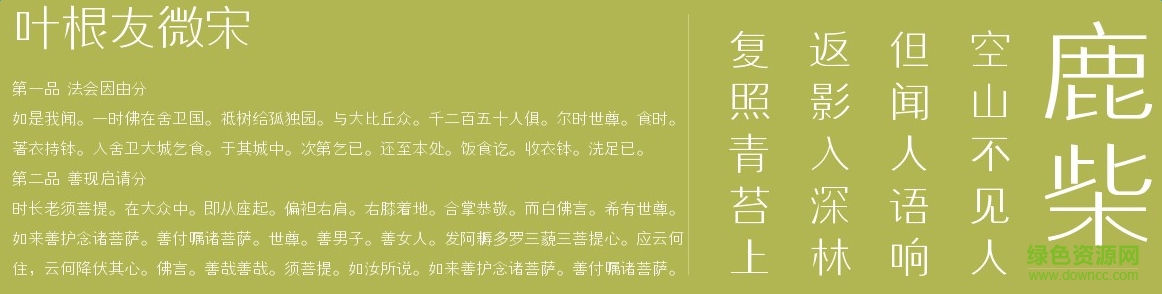
葉根友微宋字體是一款由知名書(shū)法家葉根友創(chuàng)造的字體,適用于、字體排版、印刷等方面,有需要的朋友們不要錯(cuò)過(guò)了。小編為大家提供免費(fèi)下載地址。歡迎大家來(lái)綠色資源網(wǎng)踴躍下載哦!
葉根友微宋字體,2016年度最新發(fā)布的字體,是一款柔性的字體,比較適合內(nèi)文排版和追求時(shí)尚一族的應(yīng)用,圓潤(rùn)的筆畫(huà)線(xiàn)條是這款葉根友微宋晴雅字體的特征,希望大家喜歡。
葉根友微宋字體,用途廣泛,是葉根友先生的印刷字體,字體非常纖細(xì),適用于文字排版等方面。各位字體收藏者可以來(lái)看看。